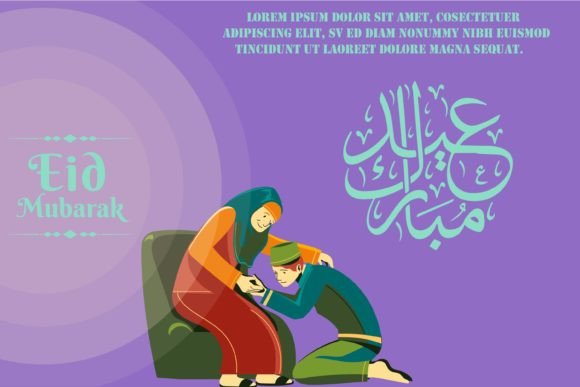
Greeting Card Tosqa Font
適切なデザイン要素を見つけるのは難しい場合がありますが、Greeting Card Tosqa Fontは作品を即座に引き立てる優れたコレクションを提供します。
精密に作られたGreeting Card Tosqa Fontは、クリーンなベクター、滑らかなタイポグラフィ、そして安心のための商用ライセンスを提供します。
POD(オンデマンド印刷)製品、結婚式の招待状、またはソーシャルメディアのグラフィックを作成している場合でも、Greeting Card Tosqa Fontは理想的です。